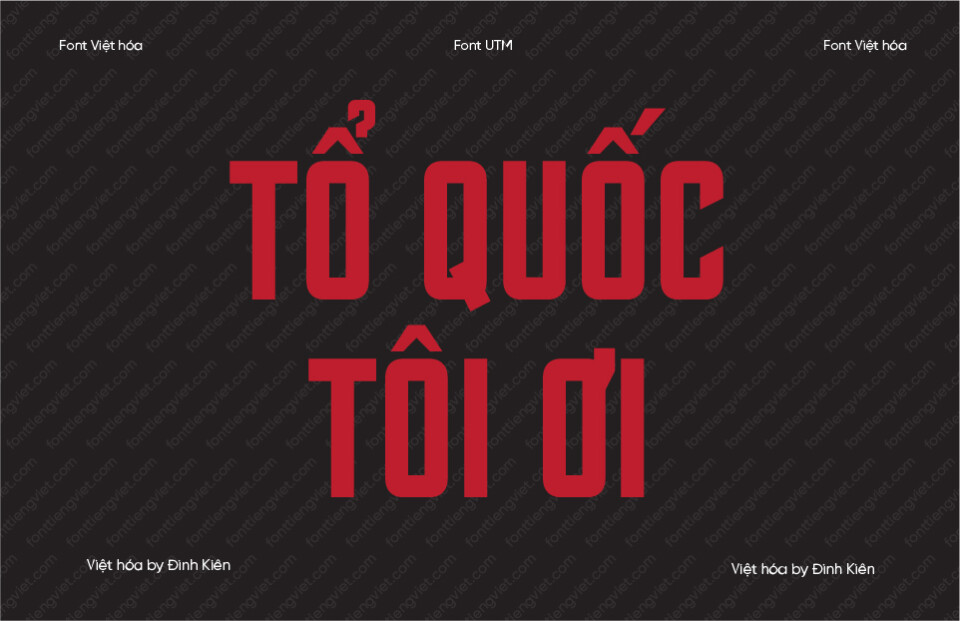
Trong thế giới thiết kế đồ họa đầy màu sắc và không ngừng phát triển, việc lựa chọn một bộ Font Chữ không chỉ đơn thuần là tìm kiếm một kiểu chữ đẹp mà còn là việc truyền tải thông điệp, tinh thần và ý nghĩa. Và trong số rất nhiều lựa chọn ấy, Font Việt hóa UTM Horizon – Quốc khánh Đại lễ Giải phóng đã nổi lên như một biểu tượng đặc biệt, mang trong mình không chỉ vẻ đẹp hiện đại mà còn là niềm tự hào dân tộc sâu sắc. Bộ font này không chỉ là một công cụ thiết kế mà còn là một tác phẩm nghệ thuật, kết hợp hoàn hảo giữa tính thẩm mỹ và giá trị văn hóa, làm say lòng bất kỳ ai đam mê sáng tạo và yêu mến những giá trị Việt Nam.
UTM Horizon Việt hóa – Biểu Tượng Của Tinh Thần Việt
Font UTM Horizon Việt hóa là một trong những sản phẩm độc đáo của cộng đồng thiết kế Việt Nam, được chỉnh sửa và tối ưu hóa để phù hợp hoàn hảo với hệ thống chữ cái tiếng Việt. Sự ra đời của nó không chỉ lấp đầy khoảng trống về font chữ tiếng Việt chất lượng cao mà còn mang đến một làn gió mới, một phong cách thiết kế hiện đại, mạnh mẽ nhưng vẫn giữ được nét mềm mại, tinh tế vốn có. Mỗi ký tự trong UTM Horizon Việt hóa đều được chăm chút tỉ mỉ, đảm bảo độ rõ ràng, dễ đọc và tính thẩm mỹ cao, phù hợp cho nhiều mục đích sử dụng khác nhau từ in ấn đến hiển thị trên màn hình.
Nguồn Gốc và Ý Nghĩa Của Font Việt hóa UTM Horizon – Quốc khánh Đại lễ Giải phóng
Điều làm cho Font Việt hóa UTM Horizon – Quốc khánh Đại lễ Giải phóng trở nên đặc biệt hơn cả chính là ý nghĩa mà nó mang trong mình. Với tên gọi gắn liền với những sự kiện trọng đại của đất nước như Quốc khánh và Đại lễ Giải phóng, bộ font này không chỉ là một công cụ thiết kế mà còn là một lời nhắc nhở về lịch sử hào hùng, về tinh thần độc lập, tự do và sự đoàn kết của dân tộc Việt Nam. Nó thể hiện lòng biết ơn sâu sắc đối với các thế hệ cha ông đã hy sinh vì nền hòa bình, tự do hôm nay. Khi sử dụng font này, người thiết kế không chỉ tạo ra những tác phẩm đẹp mà còn góp phần lan tỏa những giá trị văn hóa, lịch sử tốt đẹp đến cộng đồng.
Sự kết hợp giữa vẻ đẹp hiện đại của UTM Horizon và ý nghĩa lịch sử sâu sắc đã tạo nên một bộ font có sức hút khó cưỡng. Nó không chỉ được ưa chuộng trong các dự án thiết kế mang tính kỷ niệm, các sự kiện văn hóa, lễ hội mà còn được sử dụng rộng rãi trong các ấn phẩm truyền thông, giáo dục, nơi cần sự trang trọng, ý nghĩa nhưng vẫn đảm bảo tính thẩm mỹ cao. Đây chính là yếu tố làm nên sự khác biệt và vị thế độc tôn của font chữ này trong lòng những người yêu thiết kế tại Việt Nam.
Ứng Dụng Đa Dạng Của Font UTM Horizon Việt Hóa
Với thiết kế linh hoạt và khả năng tương thích cao, Font UTM Horizon Việt hóa có thể được ứng dụng trong vô vàn lĩnh vực. Từ việc thiết kế các poster, banner quảng cáo cho các sự kiện lớn, cho đến việc tạo ra các ấn phẩm truyền thông nội bộ, các bài thuyết trình chuyên nghiệp, hay thậm chí là trong các dự án thiết kế website, ứng dụng di động. Sự đa dạng trong ứng dụng của nó chứng tỏ tính hữu ích và khả năng thích nghi tuyệt vời với mọi yêu cầu thiết kế khắt khe nhất. Đặc biệt, trong các dịp lễ lớn của đất nước, font chữ này càng trở nên phù hợp để truyền tải thông điệp một cách trang trọng và đầy cảm xúc.
Các trường học và sinh viên cũng có thể tận dụng font chữ này để thiết kế các báo cáo, dự án học tập, hoặc các ấn phẩm kỷ niệm của trường. Đối với các bạn học sinh cấp 3 chuẩn bị cho các kỳ thi tốt nghiệp quan trọng, việc sử dụng một font chữ rõ ràng, dễ đọc như UTM Horizon Việt hóa trong các tài liệu ôn tập cũng có thể giúp tăng cường hiệu quả học tập và ghi nhớ thông tin. Nó không chỉ là một font chữ mà còn là một công cụ giúp nâng cao chất lượng truyền đạt thông tin.
Tại Sao Font Việt hóa UTM Horizon – Quốc khánh Đại lễ Giải phóng Lại Được Yêu Thích?
Sở dĩ Font Việt hóa UTM Horizon – Quốc khánh Đại lễ Giải phóng nhận được sự yêu mến rộng rãi là bởi những đặc tính nổi bật của nó. Thứ nhất, nó mang lại vẻ đẹp hiện đại, chuyên nghiệp, phù hợp với xu hướng thiết kế toàn cầu. Thứ hai, khả năng Việt hóa hoàn hảo giúp font chữ hiển thị tốt với các dấu tiếng Việt, tránh được lỗi hiển thị và đảm bảo tính thẩm mỹ cao. Thứ ba, và quan trọng nhất, là ý nghĩa lịch sử, văn hóa mà nó truyền tải. Nó không chỉ là một font chữ, mà còn là một câu chuyện, một niềm tự hào. Sự kết hợp này đã tạo nên một công cụ thiết kế mạnh mẽ, có khả năng chạm đến cảm xúc của người xem.
Đối với các nhà thiết kế, việc sử dụng font chữ này không chỉ giúp tác phẩm trở nên nổi bật mà còn thể hiện sự tôn trọng đối với văn hóa và lịch sử dân tộc. Đây là một điểm cộng lớn trong bối cảnh toàn cầu hóa, khi mà các giá trị bản sắc địa phương ngày càng được đề cao. Hơn nữa, font chữ này còn góp phần nâng cao chất lượng tổng thể của các ấn phẩm, giúp thông điệp được truyền tải một cách rõ ràng, mạnh mẽ và đầy ấn tượng.
Tóm lại, Font Việt hóa UTM Horizon – Quốc khánh Đại lễ Giải phóng không chỉ là một bộ Font Chữ đẹp mắt và hiện đại mà còn là một biểu tượng mang đậm giá trị văn hóa, lịch sử của Việt Nam. Với thiết kế tinh tế, khả năng ứng dụng đa dạng và ý nghĩa sâu sắc, bộ font này chắc chắn sẽ tiếp tục là lựa chọn hàng đầu cho các nhà thiết kế, học sinh, sinh viên và những ai muốn truyền tải thông điệp một cách chuyên nghiệp và đầy cảm xúc. Hãy khám phá và trải nghiệm sức mạnh của font chữ này để tạo nên những tác phẩm độc đáo, góp phần tôn vinh những giá trị tốt đẹp của đất nước.